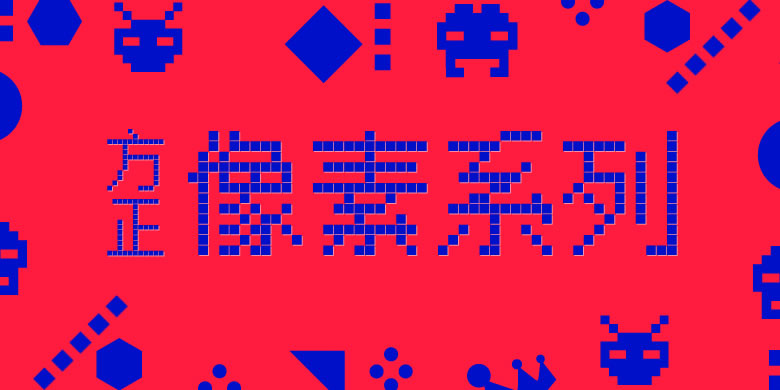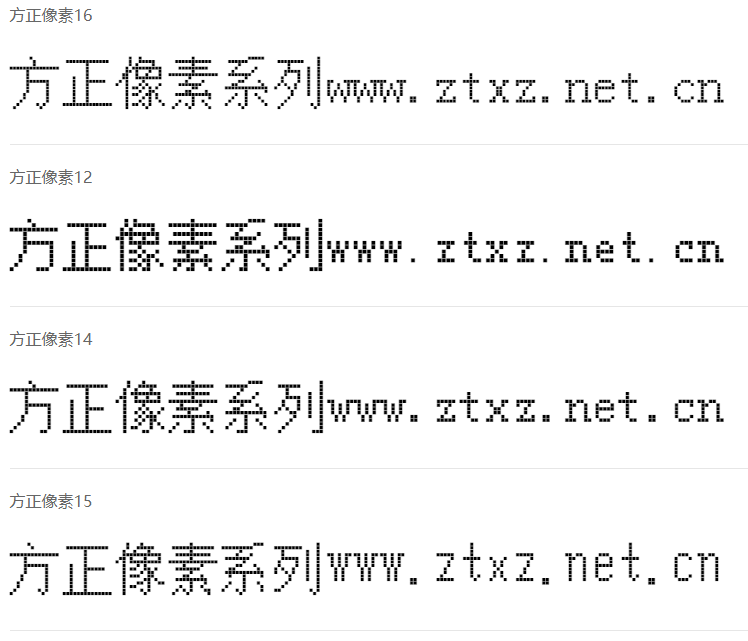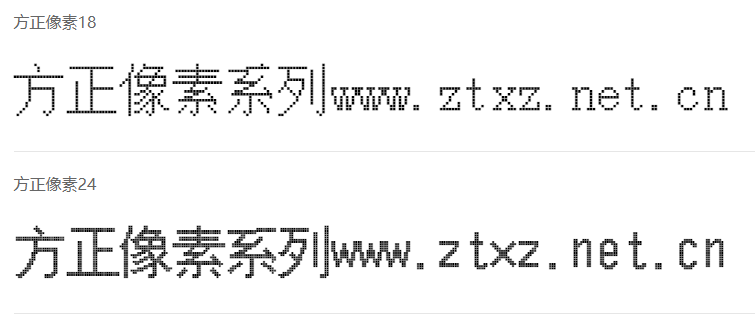
方正像素系列
方正像素是一款用于电子屏幕的功能性字体。这款字体基于黑体和宋体的基本字形,每个字的像素颗粒由手工设定,在保证易识性和美观性的同时满足屏幕设备上的点阵数量。方正像素家族包含6款字体,其中数字代表最长边的点阵数,适用于LED屏和针式打印机等设备。此外,小字号的方正像素具有一定的易读性,还可在传统印刷媒介中用于机械和科技类的文本。